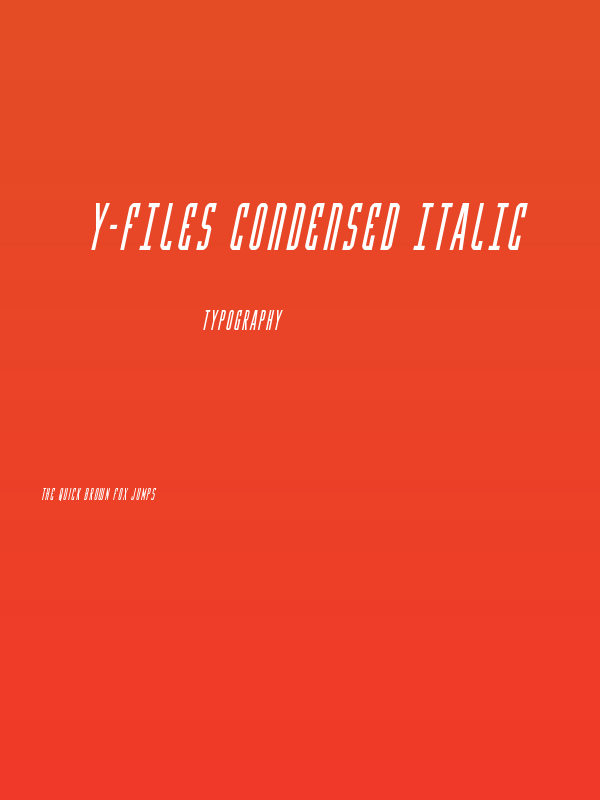
Y-Files Condensed Italic Font
✎ Sci-fi
| Progetti proposti | Ideal for use in headlines, posters, branding, and advertising where a modern and impactful look is desired. |